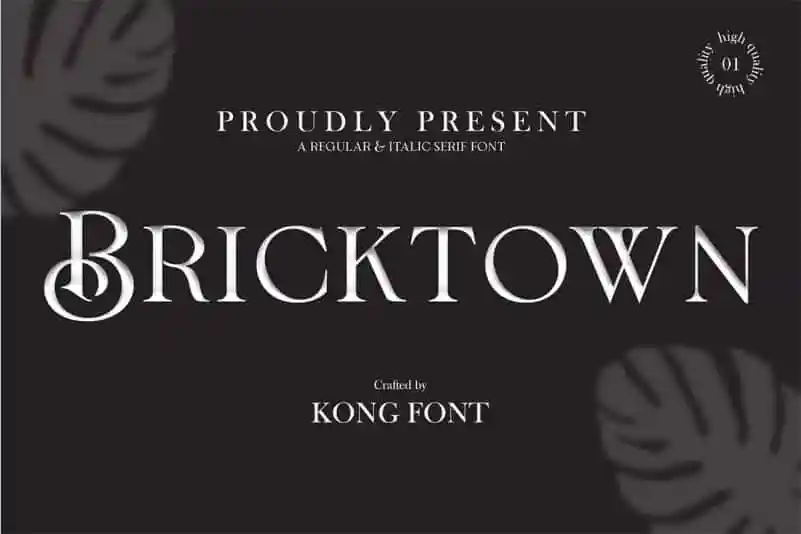
Bricktown Serif Font – Download Grátis
Bricktown Serif é uma elegante serif clássica que incorpora um toque de originalidade. Essa fonte vem com ligaduras que adicionam um tom de interesse a qualquer tipo de design. Ela foi criada e compartilhada por fontkong, oferecendo ao designer uma sensação autêntica. Aproveite esta font para criar cartões de aniversário encantadores, arte de estacionamento delicada, postagens sociais impactantes e cartas de cumprimento simpáticas. Toda sua essência elegante é o suficiente para transformar qualquer projeto em algo que você gostaria de compartilhar conosco.